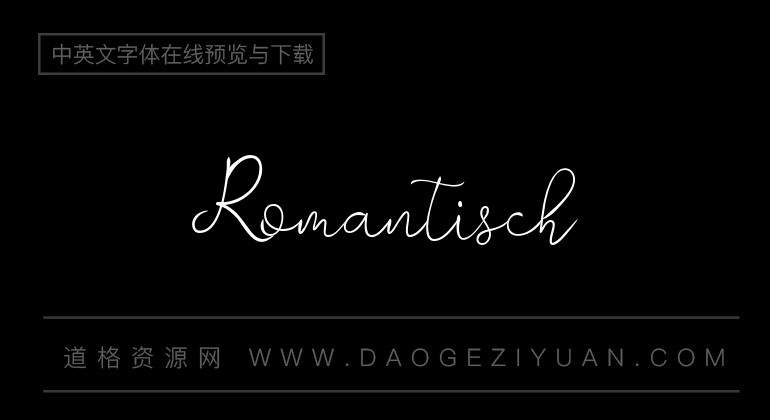
Romantisch
Romantisch 字体是一种欧洲字体风格,由德国印刷师和书法家在 19 世纪创建。它以古典的线条和精致的花纹为特征,具有浪漫优雅的气质,可以用来创作浪漫的文字作品。它的特点是古典的字体风格和温柔的色调,可以用来表达浪漫的情感,也可以用来表达更加优雅的情感。
Romantisch是一款非常不错的手写艺术字体,具有很好的视觉感,适合于文化类的宣传设计、商业类品牌的广告和产品包装设计以及个性化文字排版等较多场景。